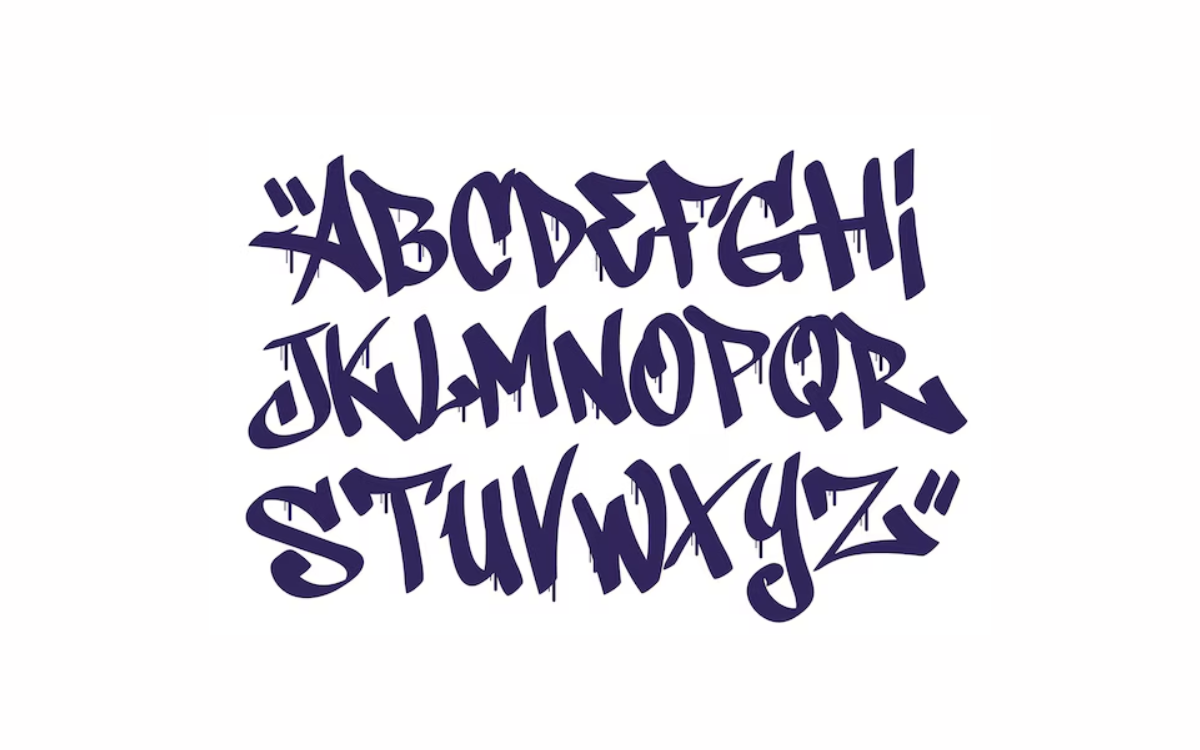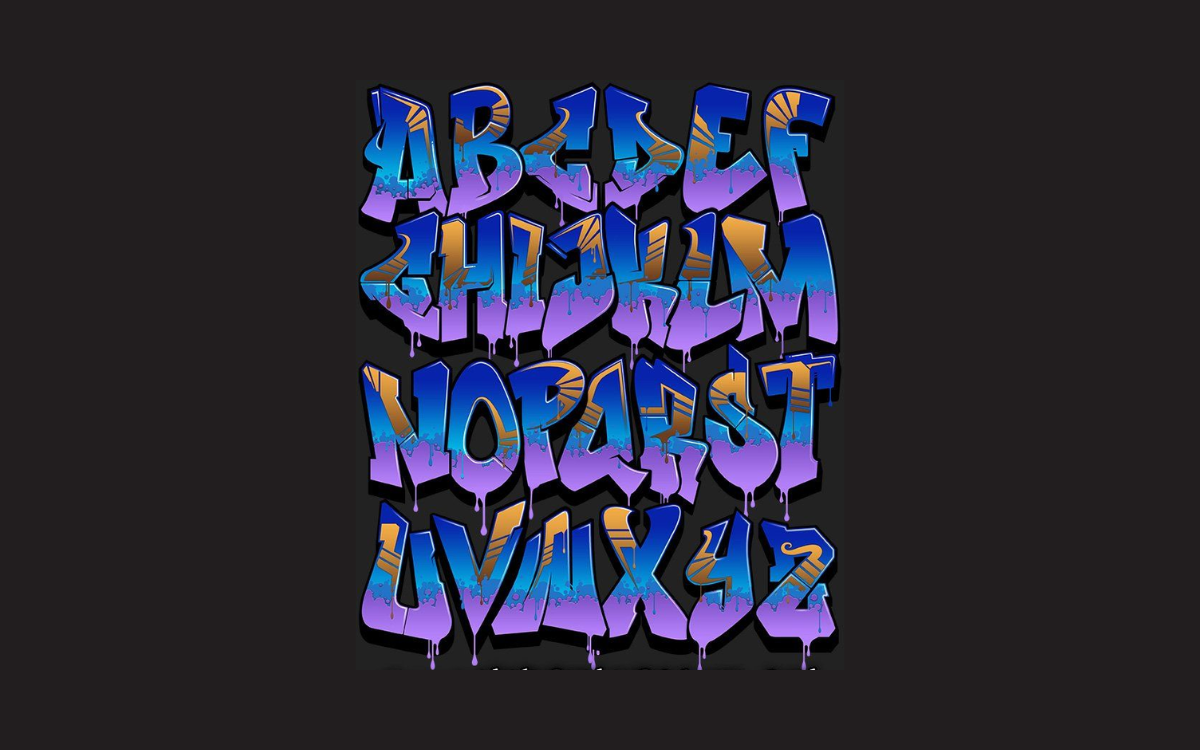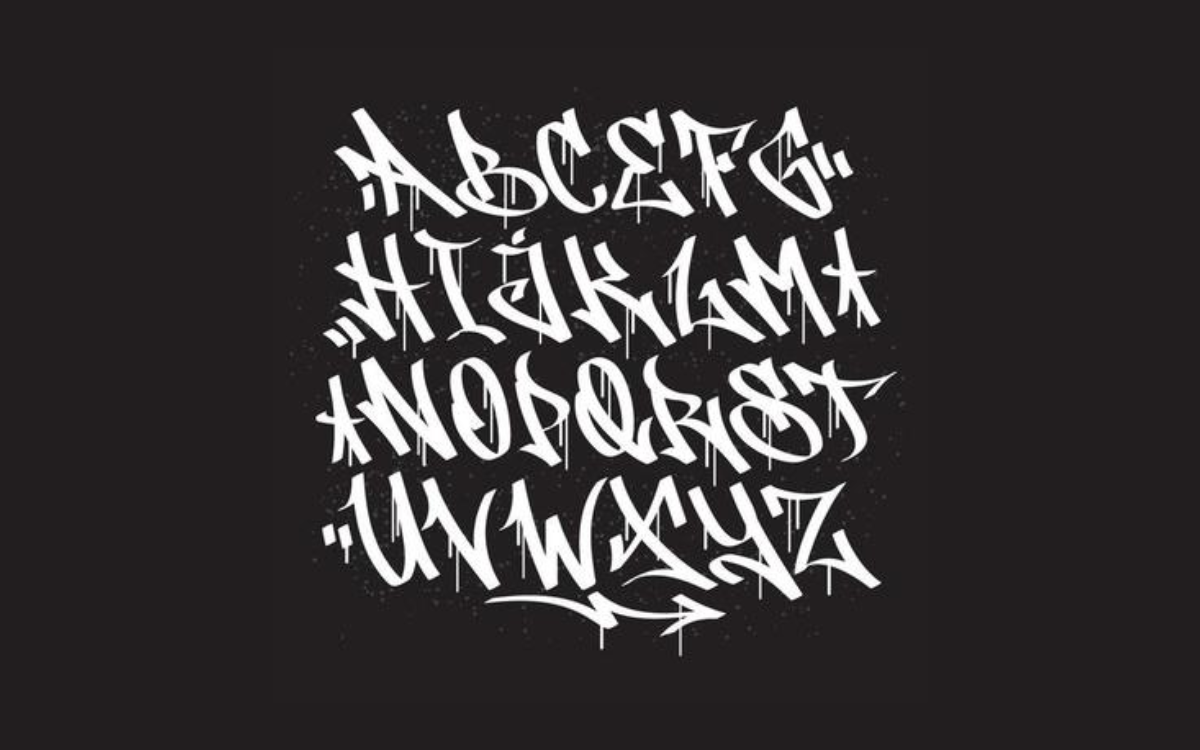
Font Graffiti Free
Phân loại: Đường phố
Kiểu chữ: Display
Độ dày: Regular, Bold
Font Graffiti thường mô phỏng phong cách viết chữ đường phố, thể hiện qua các đường nét táo bạo, ngẫu hứng và sáng tạo. Những font chữ này thường có kiểu dáng đậm, đôi khi hơi méo mó, với các đường cong và góc cạnh mang tính nghệ thuật cao. Font graffiti thuộc bộ font chữ trang trí được sử dụng phổ biến trong các thiết kế liên quan đến văn hóa đường phố, hip-hop, hoặc các dự án cần đến phong cách mạnh mẽ và phá cách. Các ví dụ điển hình của font graffiti bao gồm “Urban Jungle,” “Graffiti Classic,” và “Tagster.” Những font này thường giúp tạo nên không gian thị giác đậm chất đường phố và nghệ thuật ngầm.